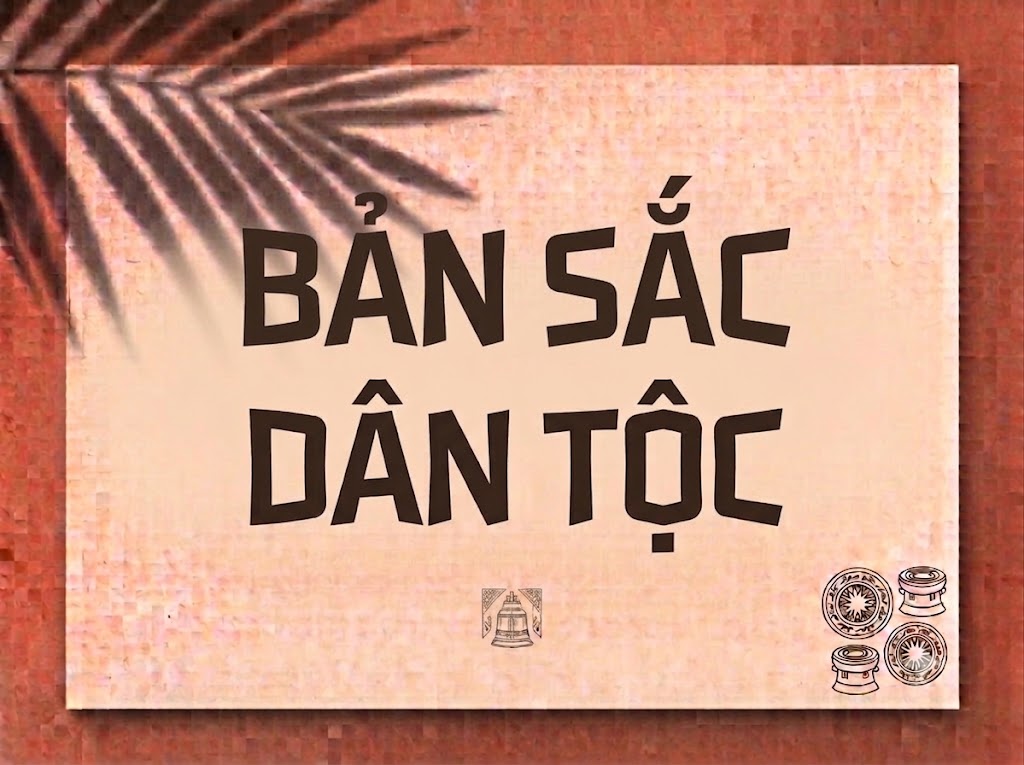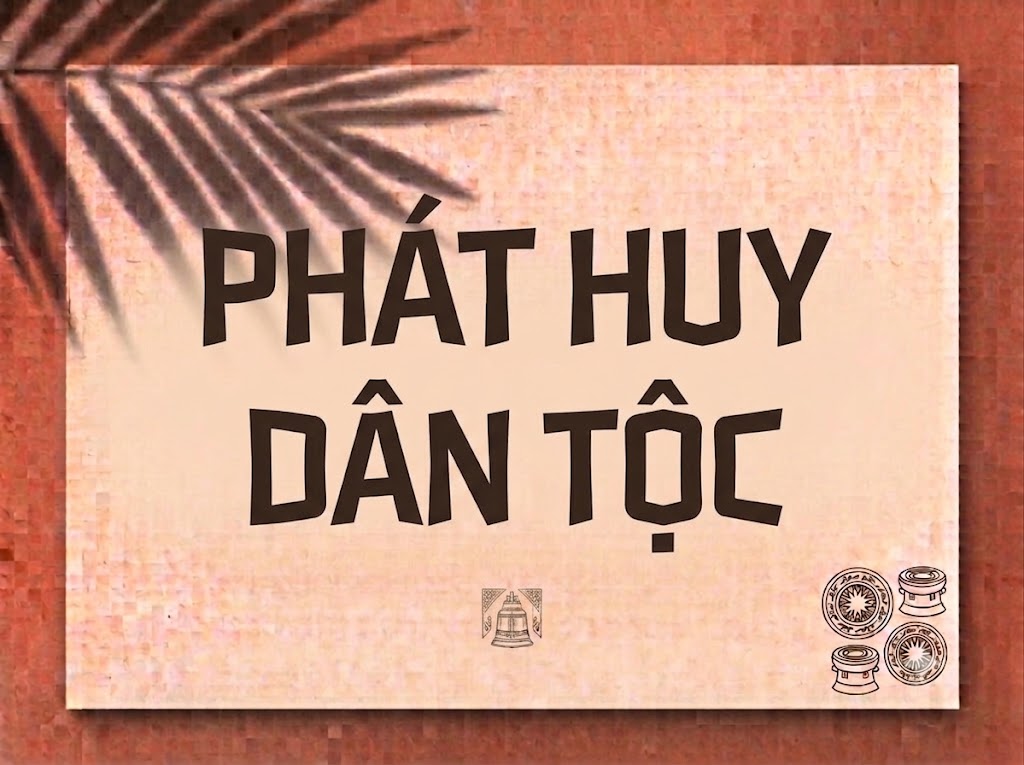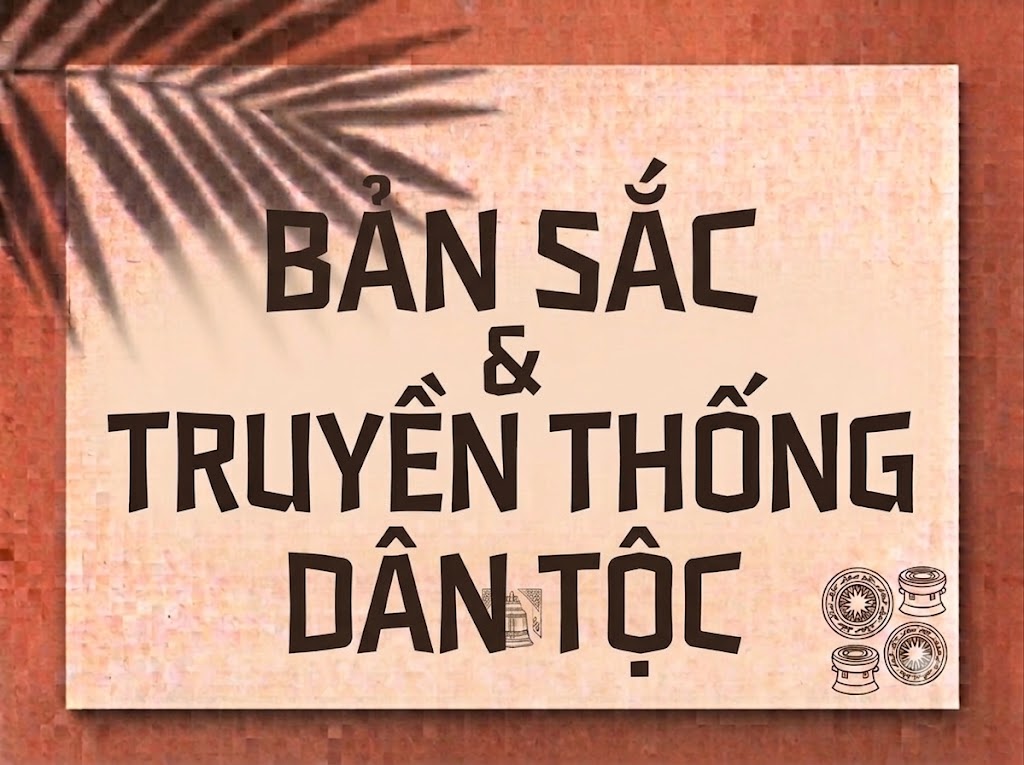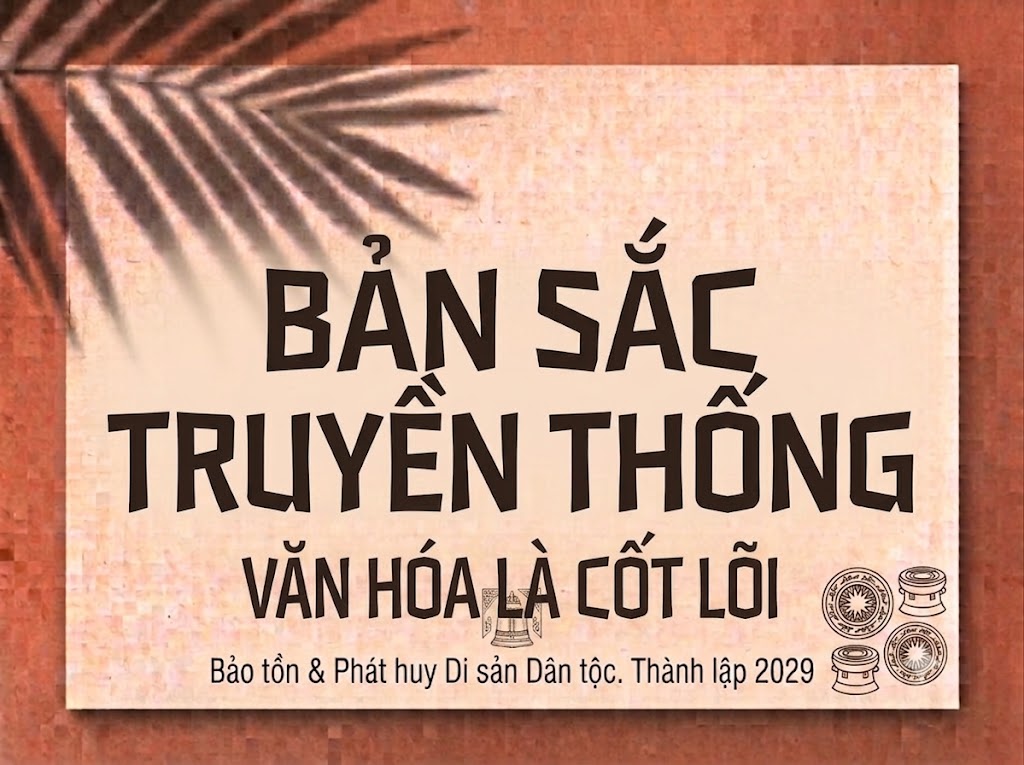
1FTV Akisa
Trong không gian sáng tạo nội dung số, đặc biệt là các phân khúc năng động như thể thao điện tử (esports), công nghệ tương lai hay thời trang đường phố, một tiêu đề mờ nhạt sẽ tự động làm giảm đi sức hút của toàn bộ ấn phẩm. Để tạo ra cú hích thị giác mạnh mẽ, các nhà thiết kế luôn săn đón những phông chữ hiển thị sở hữu kết cấu khối dày dặn, bứt phá và mang tính độc bản cao.
Nếu bạn đang tìm kiếm một giải pháp typographic mang tinh thần chiến binh, hầm hố và đậm chất cơ khí hoặc viễn tưởng để làm nổi bật các dòng headline quảng cáo, banner giải đấu hay video ngắn, thì font 1FTV Akisa chính là câu trả lời lý tưởng.
Giới thiệu về font 1FTV Akisa
Font 1FTV Akisa là một bộ chữ hiển thị (display font) không chân sở hữu phong cách thiết kế hình học góc cạnh, mạnh mẽ, gợi liên tưởng đến cấu trúc mecha (robot), cyberpunk và thế giới trò chơi điện tử hiện đại.
Tên phông chữ: 1FTV Akisa
Nhờ nền tảng kỹ thuật đồng bộ này, phông chữ mang lại khả năng co giãn bố cục vô cùng linh hoạt. Bạn có thể tự tin ứng dụng trên mọi phần mềm đồ họa chuyên nghiệp và ứng dụng dựng phim mà không lo gặp phải hiện tượng lỗi răng cưa hay vỡ nét khi phóng lớn chữ ở các dòng headline chính.
Đặc điểm nổi bật của phong cách thiết kế Akisa
Sức hút thị giác đầy uy lực của font 1FTV Akisa đến từ sự phá cách táo bạo trong cấu trúc hình khối và các đường cắt dứt khoát:
Kết cấu chữ dày dặn, vững chãi: Độ dày nét lớn (heavy bold) tạo ra sức nặng truyền thông cực lớn, giúp dòng tiêu đề của bạn ngay lập tức chiếm trọn tiêu điểm của ấn phẩm.
Đường cắt và gai góc hình học độc đáo: Các ký tự được xây dựng từ những mảng khối vuông vắn, đan xen khéo léo với các góc vát xiên phẳng phiu và các chi tiết nhọn nhẹ ở thân chữ (như ở chữ k, r, x, f). Sự chấm phá này tạo nên diện mạo vừa gai góc, nổi loạn, lại vừa mang hơi hướng công nghệ tech-wear thời thượng.
Phom dáng đồng đều và thông thoáng: Khoảng trống nội tại bên trong các ký tự (counter) được tính toán tỉ mỉ, giúp các chữ cái khi đứng cạnh nhau tạo thành một khối chữ ngăn nắp, kiên cố như một bức tường thành mà không hề gây cảm giác ngột ngạt khi nhìn từ xa.
Hệ thống khoảng cách chữ (kerning) và độ giãn dòng đã được căn chỉnh chuẩn xác đến từng pixel, giúp các khối chữ dày khi đứng cạnh nhau đạt được tỷ lệ vàng về mặt khoảng trống, không bị dính nét hay chồng chéo lên nhau.
Tích hợp trọn vẹn bộ chữ cái hoa và thường đồng bộ, dãy chữ số từ 0-9 dáng khối vững chãi cùng hệ thống các ký tự đặc biệt, dấu câu thông dụng.
Bản Việt hóa chuẩn chỉnh từ đội ngũ 1FTV giúp các nhà sáng tạo nội dung hoàn toàn yên tâm thiết kế các văn bản tiếng Việt có dấu phức tạp mà không lo gặp phải tình trạng nhảy font hay hiển thị thiếu ký tự dấu câu khó chịu.
Hình ảnh demo thực tế của font 1FTV Akisa
Để giúp bạn dễ dàng đánh giá khả năng hiển thị trực quan và co giãn linh hoạt của phông chữ này trên các tỷ lệ kích thước khác nhau, hãy cùng xem qua bảng mô phỏng thực tế từ file hệ thống image_c44f4e.png:
Kích thước nhỏ (12pt – 24pt): Nhờ cấu trúc hình học đứng dáng và khoảng hở chữ thông thoáng, dãy chữ cái và hệ thống chữ số vẫn hiển thị ngay ngắn, rành mạch và dễ nhìn trên giao diện thiết bị di động.
Kích thước lớn (36pt – 72pt): Đây chính là đất diễn đỉnh cao nhất để font chữ phô diễn toàn bộ sự hầm hố, góc cạnh đầy uy lực, tạo hiệu ứng thị giác bùng nổ chiếm trọn tâm trí người xem.
Ứng dụng của font Akisa trong thiết kế đồ họa và làm video
Sở hữu nét cá tính hầm hố, mạnh mẽ và kết cấu khối vững chãi, font 1FTV Akisa mở ra không gian sáng tạo vô cùng rộng lớn cho các dự án truyền thông thế hệ mới:
Làm tiêu đề cho video ngắn (TikTok, Reels, Shorts): Dáng chữ khối đứng, sắc nét này là lựa chọn tuyệt vời để làm các cụm từ khóa chính giật tít ở phần mở đầu video. Độ bắt mắt của chữ giúp giữ chân người xem lướt feed dừng lại ngay lập tức, đồng thời hiển thị cực kỳ nổi bật trên các khung hình đứng 9:16 của thiết bị di động.
Thiết kế ảnh thu nhỏ YouTube (Thumbnail): Vũ khí hạng nặng để bứt phá tỷ lệ nhấp chuột (CTR) cho các kênh thuộc chủ đề gaming, thể thao điện tử (esports), review đồ công nghệ, xe cộ, phim hành động hoặc các video thử thách ngắn nhờ độ hiển thị trực diện từ khoảng cách xa.
Banner và Poster quảng cáo ngành giải trí, thể thao: Cực kỳ hoàn hảo cho các poster giải đấu game, banner câu lạc bộ gym, fitness, biểu ngữ cho các sự kiện âm nhạc điện tử (EDM) sôi động của giới trẻ.
Nhận diện thương hiệu phong cách Streetwear & Tech: Phù hợp làm logo dạng chữ khối, thiết kế nhãn mác bao bì sản phẩm, hoặc thiết kế các artwork in ấn độc lạ trên áo thun cho các local brand hướng tới sự cá tính, nam tính và phá cách.